Tuyển tập 13 font chữ đẹp trong Word đã được Việt hóa chưa chắc bạn đã biết
Lựa chọn giữa vô vàn các font chữ đẹp trong Word sẽ khiến bạn tốn kha khá thời gian và công sức đấy. Thay vào đó, hãy thử tham khảo những font chữ thu hút, ấn tượng và được nhiều người dùng ưa chuộng mà FPT Shop đã tổng hợp sẵn trong bài viết dưới đây nhé!
Bạn đang tìm các font chữ đẹp trong Word? Có quá nhiều font chữ khiến bạn hoang mang không biết phải lựa chọn thế nào? Vậy thì hãy để FPT Shop gợi ý cho bạn 13 font chữ ấn tượng, có tính ứng dụng cao để phục vụ cho quá trình soạn thảo và thiết kế văn bản nhé!
Các font chữ thanh lịch, tối giản trong Word
1. Font chữ Be Vietnam
Be Vietnam là một cái tên không còn xa lạ đối với nhiều người. Không cần quá cầu kỳ, font chữ này ghi điểm bởi vẻ đẹp tinh tế, thanh lịch và tối giản. Nhờ vậy, Be Vietnam trở thành lựa chọn hoàn hảo cho đa dạng các loại văn bản, từ bài báo, email cho đến sách điện tử và website.
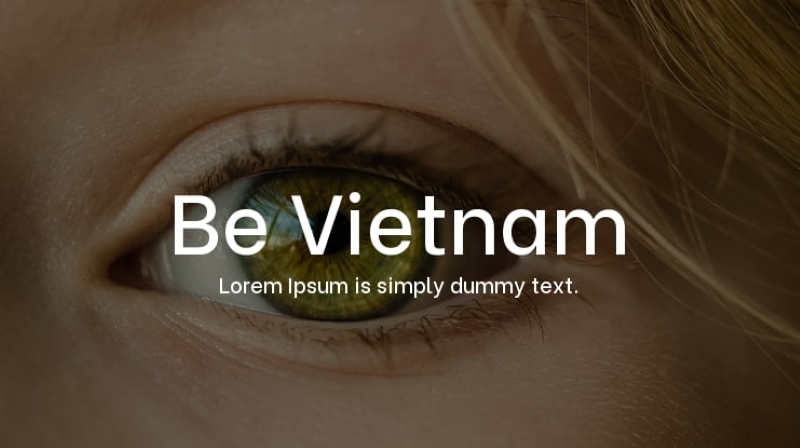
2. Font chữ Roboto
Roboto là một trong những font chữ đẹp trong Word được sử dụng phổ biến hiện nay. Đây là dạng font chữ không chân (sans-serif) được thiết kế bởi Christian Robertson, nhà thiết kế giao diện của Google. Roboto sở hữu đường nét hiện đại, rõ ràng và dễ đọc. Nhờ sở hữu giao diện thân thiện, cởi mở nên font chữ này thường sử dụng rộng rãi trong nhiều loại văn bản khác nhau.
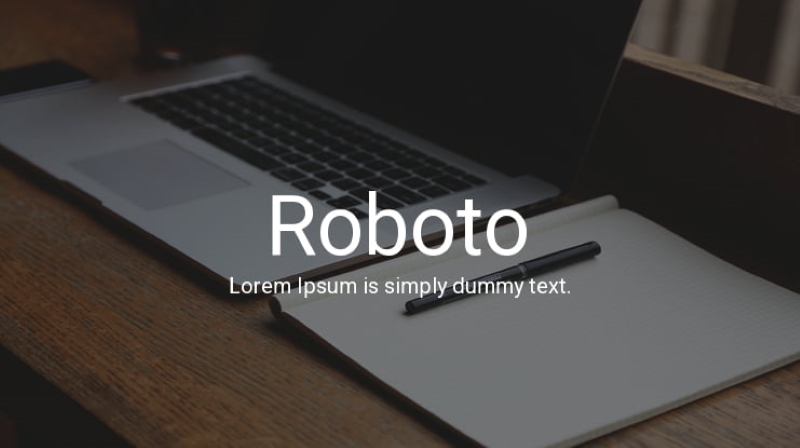
3. Font chữ Source Sans Pro
Source Sans Pro là một font chữ sans-serif được ưa chuộng trong nhiều văn bản bởi sự đơn giản, dễ nhìn và tính ứng dụng cao. Font chữ này được thiết kế bởi Paul D. Hunt, một nhà thiết kế đồ họa tài năng đến từ Adobe. Source Sans Pro là lựa chọn hoàn hảo cho những ai yêu thích sự tinh tế và thanh lịch.
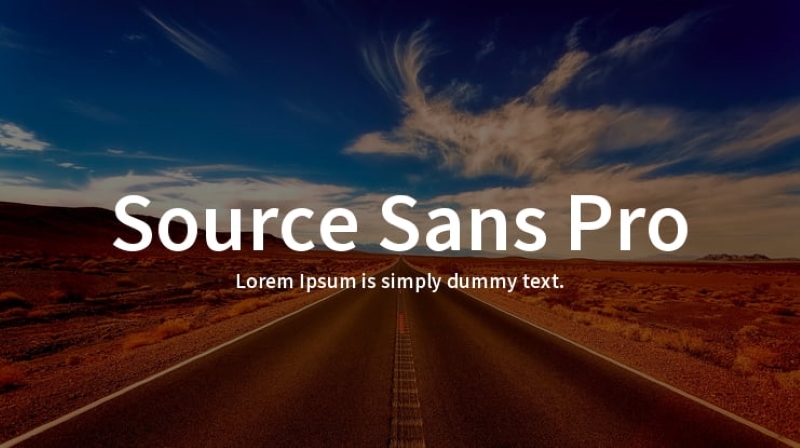
4. Font chữ Open Sans
Open Sans được đánh giá cao bởi tính đơn giản, hiện đại và dễ đọc. Đây là một font chữ sans-serif sở hữu thiết kế trẻ trung và có độ sắc nét cao nên được ưa chuộng để soạn thảo trong nhiều văn bản Word.
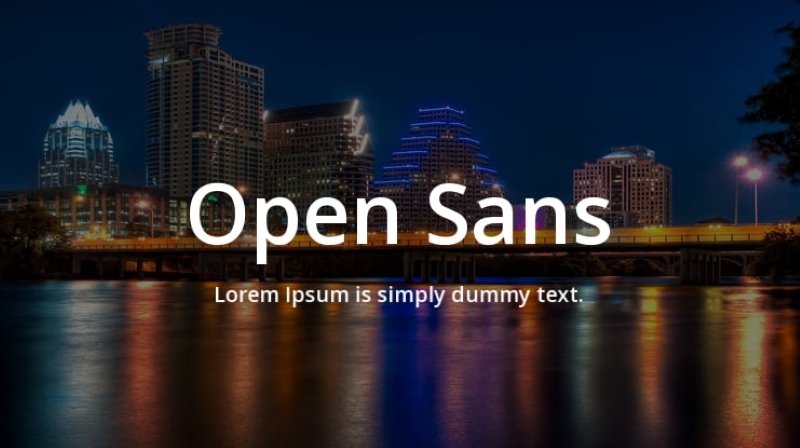
5. Font chữ Playfair Display
Playfair Display là font chữ thuộc họ serif với các nét thanh và nét đậm xen kẽ nhau một cách hài hòa. Vì vậy mà Playfair Display mang một vẻ ngoài thanh mảnh, tinh tế, sang trọng và thu hút. Font chữ này phù hợp với các loại văn bản quan trọng, mang tính chất chuyên nghiệp. Tuy nhiên, Playfair Display có một nhược điểm nhỏ, đó là khá khó đọc nếu áp dụng cho những đoạn văn bản nhiều chữ.
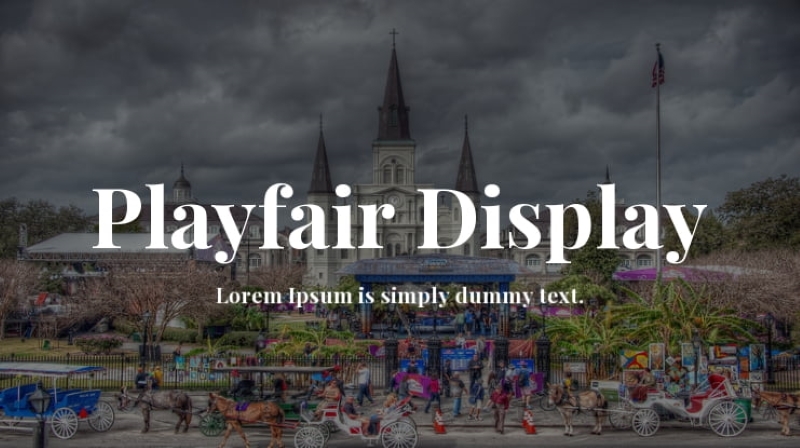
6. Font chữ Roboto Slab
Roboto Slab là một font chữ đẹp trong Word được phát triển bởi Google và thiết kế dựa trên font chữ Roboto phổ biến nhưng với các đường nét serif được thêm vào để tạo cảm giác thanh lịch và tinh tế hơn. Roboto Slab sở hữu vẻ đẹp mềm mại, uyển chuyển, tạo cảm giác thân thiện và cởi mở. Font chữ này mang phong cách hiện đại, tối giản và phù hợp với nhiều dạng văn bản khác nhau trong Word.
7. Font chữ Bitter
Bitter là một font chữ hiện đại sở hữu kiểu dáng dày dặn, tạo cảm giác mạnh mẽ và ấn tượng. Các đường nét của Bitter được thiết kế sắc nét, rõ ràng và dễ nhìn.
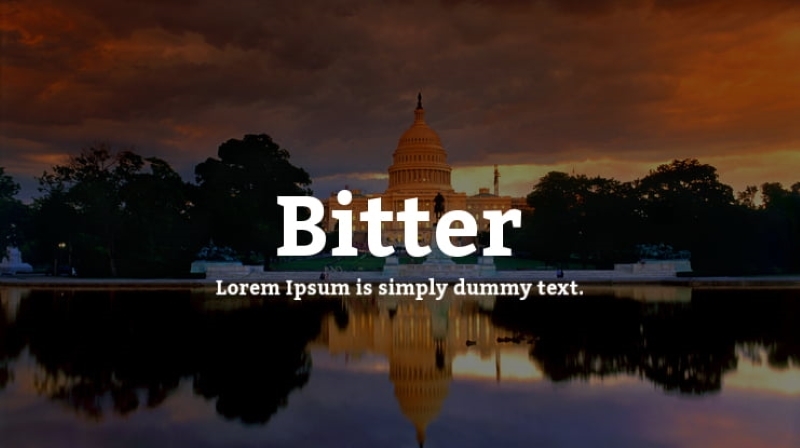
8. Font chữ Lora
Lora là kiểu serif có độ tương phản vừa phải, rất phù hợp cho các nội dung văn bản. Sở hữu những đường cong trau chuốt nên Lora mang vẻ đẹp thanh lịch, tinh tế. Font chữ này cũng được đánh giá là dễ đọc và được tối ưu khi xem trên các thiết bị màn hình.
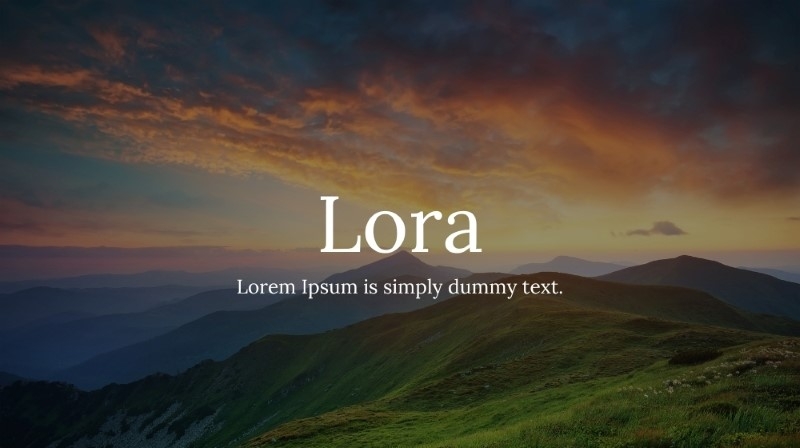
Các font chữ đẹp trong Word kiểu viết tay
1. Font chữ Pacifico
Pacifico là font chữ đẹp trong Word mô phỏng phong cách viết tay tự nhiên. Đường nét của Pacifico mềm mại, mượt mà với các đường nét đậm bo tròn và độ dày đồng đều. Sử dụng font chữ này cho các tiêu đề hoặc các đoạn văn bản ngắn sẽ tạo hiệu ứng tương phản đẹp mắt.
2. Font chữ Dancing Script
Dancing Script là font chữ khá tương đồng với chữ viết tay thực tế. Nhờ sự kết hợp tinh tế giữa nét thanh và nét đậm cũng như đường cong mềm mại, phông chữ mang vẻ đẹp trang nhã, uyển chuyển nhưng cũng đầy phá cách.
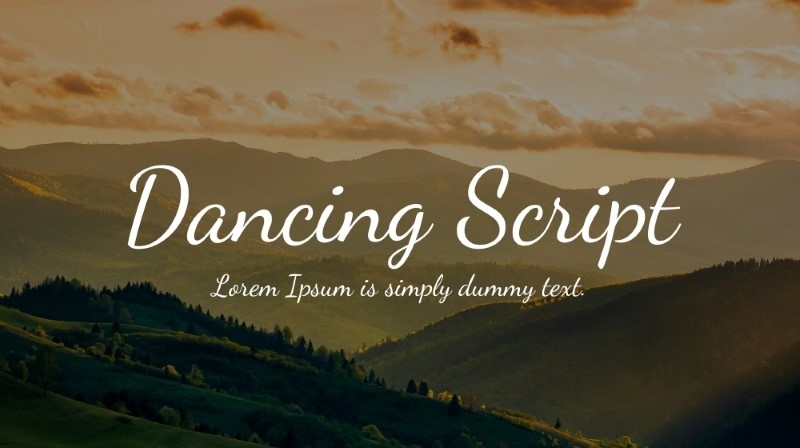
3. Font chữ Charmonman
Charmonman mang vẻ đẹp tinh tế và sang trọng, được lấy cảm hứng từ font chữ viết tay Zapfino. Charmonman sở hữu đường cong uyển chuyển, thanh thoát, tạo cảm giác mềm mại cho từng con chữ. Các chi tiết cũng được trau chuốt tỉ mỉ, thể hiện sự tinh tế và thanh lịch.
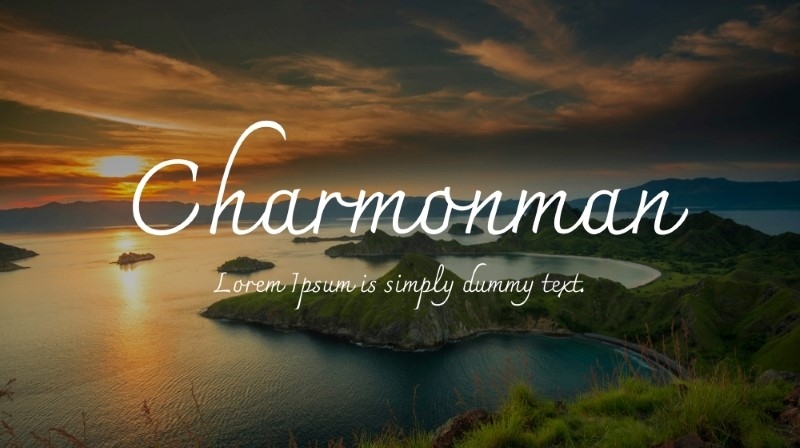
4. Font chữ Lobster
Lobster được thiết kế với đường nét mập mạp, bo tròn tạo cảm giác vui tươi, dễ thương và gần gũi. Ngoài ra, font chữ này còn sở hữu những chi tiết cách điệu tinh tế, giúp tạo điểm nhấn và khác biệt cho từng con chữ.
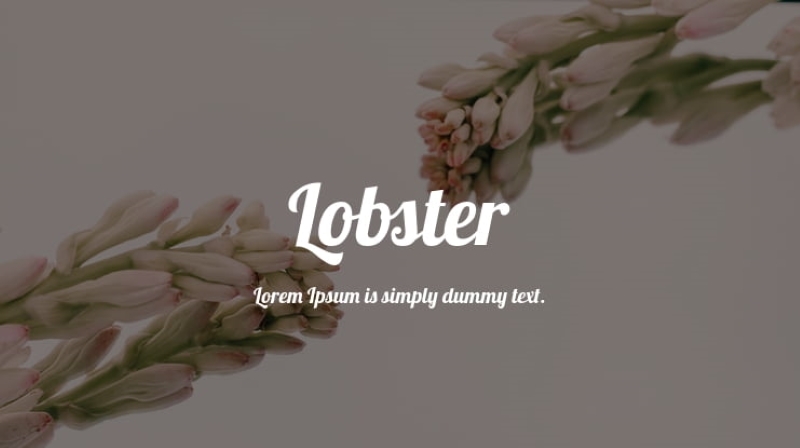
5. Font chữ Srisakdi
Srisakdi là font chữ độc đáo mang đến cho người xem cảm giác vui nhộn và thời thượng. Font chữ này được thiết kế bởi Jack Harich, một nhà thiết kế tài năng đến từ Thái Lan. Srisakdi mang phong cách hiện đại, trẻ trung với các chi tiết cách điệu tinh tế và đường nét mềm mại.
Lời kết